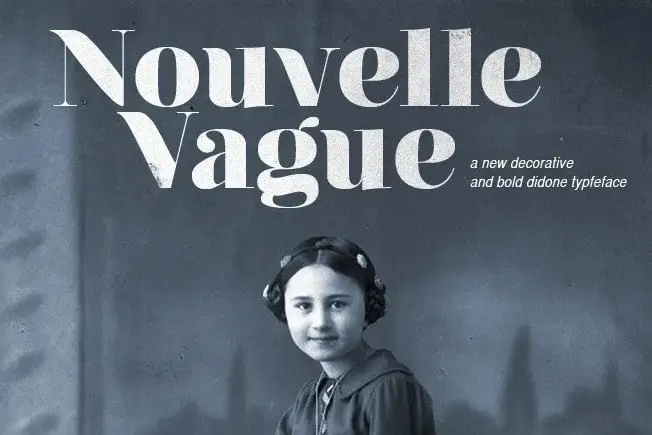
Nouvelle Vague Font – Fonte Grátis
Nouvelle Vague Font
Nouvelle Vague Font é uma tipografia serif clássica que cria um clima e desperta emoções antes mesmo de você ler o texto. Inspirada no estilo moderno e vintage, esta nova Serif foi projetada pelo Dirk Schuster. Com sua simplicidade elegante, ela se destaca como uma fonte versátil, capaz de abranger uma ampla gama de projetos desde imagens alegres em revistas, convites de casamento, marcas e até mesmo design de pôsteres. É perfeita para aqueles que buscam um toque vintage no seu trabalho sem se distanciar completamente do moderno. Este font é uma escolha certeira para quem busca personalidade e estilo em suas criações.